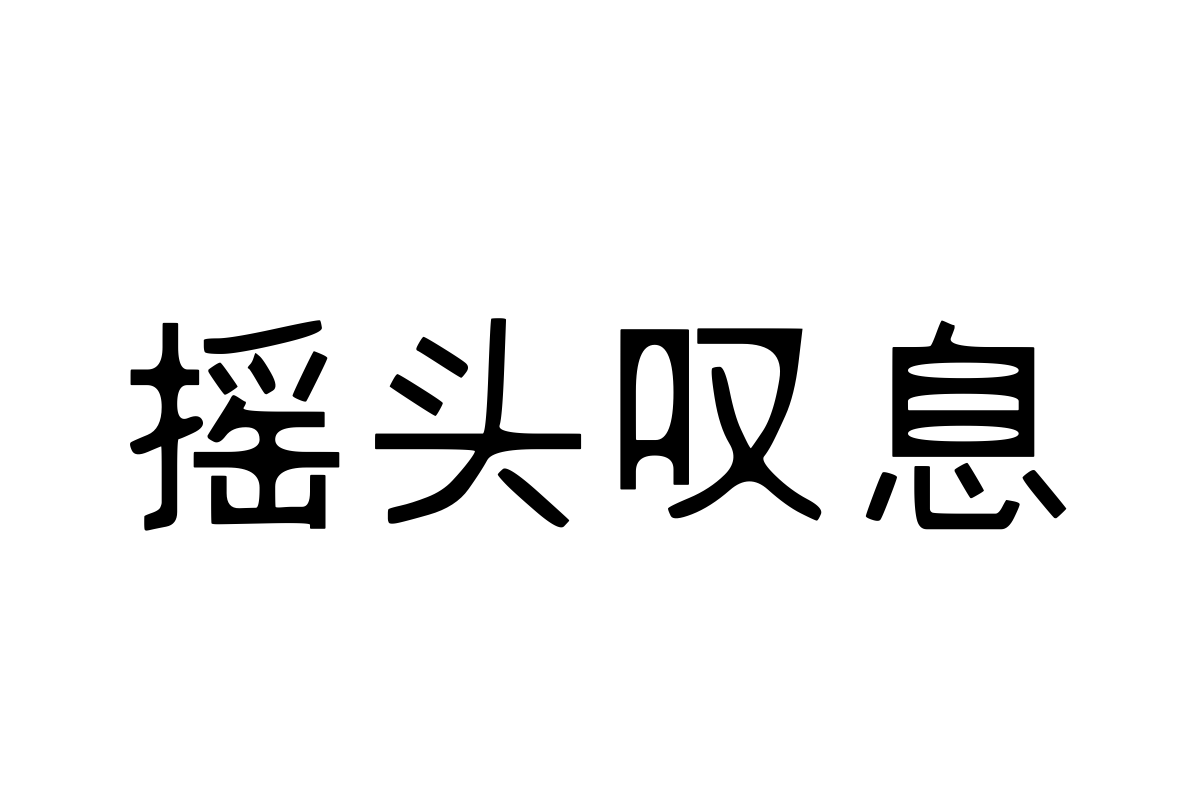
汉标电焊黑体是一款专为电焊行业设计的字体。这款字体具有以下特点:
1. 简洁明了:字体结构简洁,笔画清晰,易于阅读和识别。
2. 易读性好:字体大小适中,适合远距离观看,不易产生视觉疲劳。
3. 适应性强:适用于各种印刷材料,如纸张、塑料、金属等。
4. 专业性强:字体设计符合电焊行业的专业性要求,有助于提高焊接质量和效率。
5. 可定制性:可根据客户需求进行个性化定制,满足不同应用场景的需求。
总之,汉标电焊黑体是一款适用于电焊行业的专业字体,具有良好的易读性、适应性和专业性。